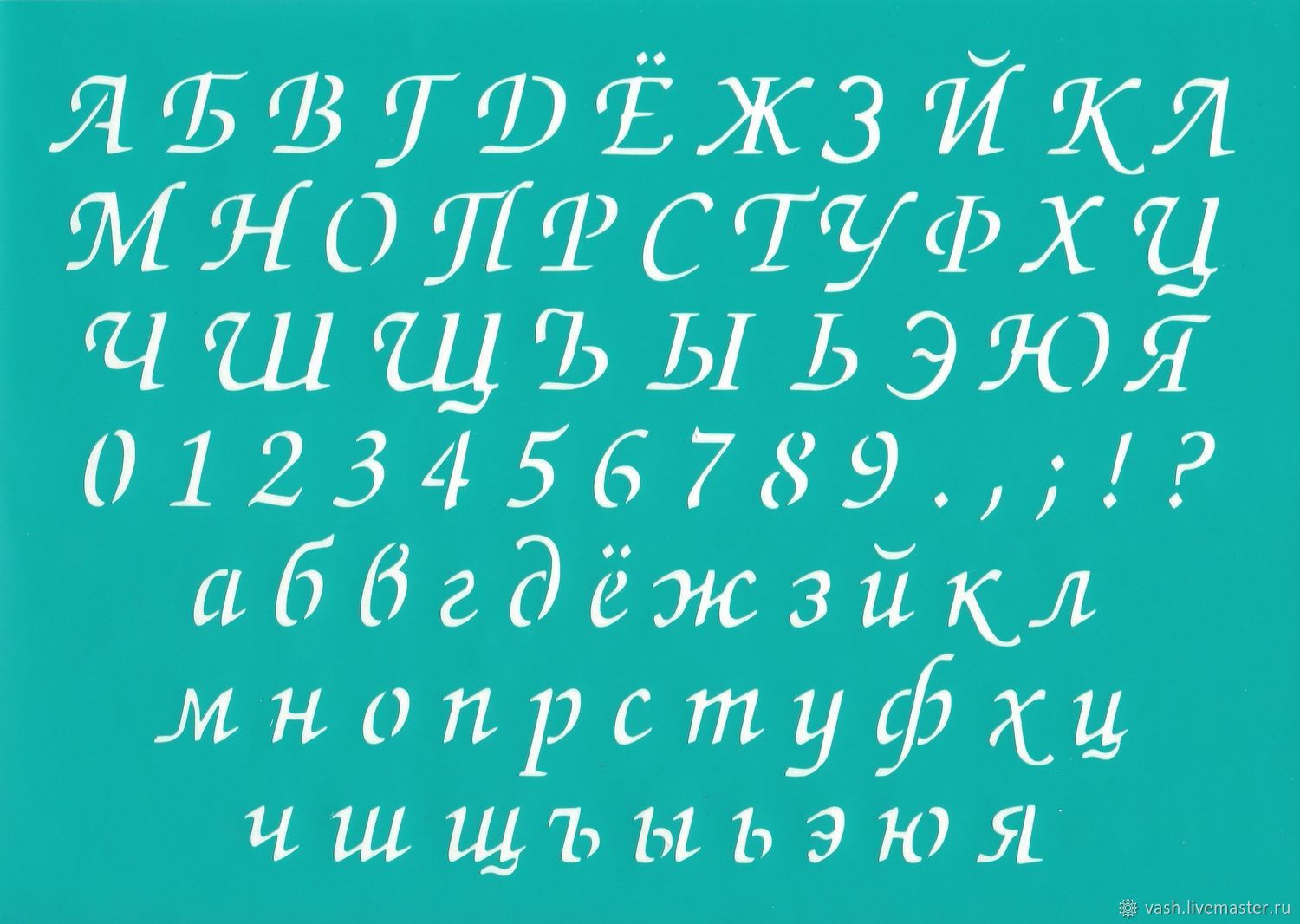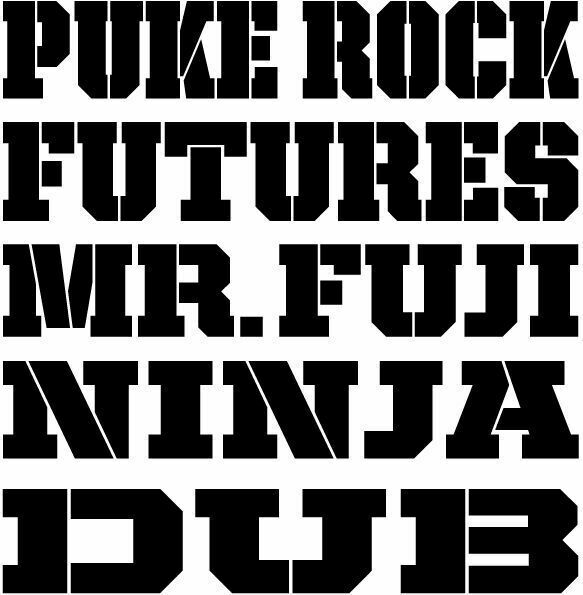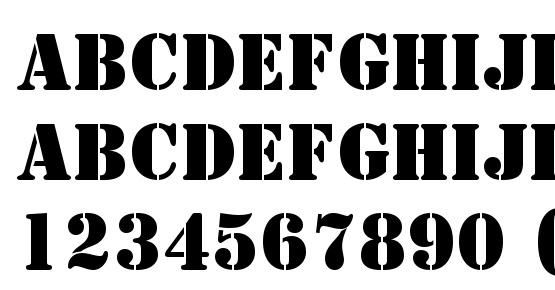
Вензельные буквы русского алфавита трафарет
Трафареты букв – это шаблон формата А4 для распечатки и вырезания из бумаги. Полученный трафарет готов для многократного использования, просто нанесите на него краску тонким слоем. Буквы алфавита в основном используются для оформления праздников, а также в рекламной индустрии и для декора своими руками.
Красивый шрифт, большие буквы, печатные и прописные вызовут неподдельный интерес у детей, начните развивать память и стимулировать творческую деятельность ребенка. Канцелярским ножом аккуратно по контуру вырежьте трафарет, покажите, как равномерно наносится краска. Это поможет сформировать первое представление об алфавите.
Трафареты и шаблоны букв русского алфавита для вырезания из бумаги помогут вам красиво и быстро нанести надпись на любую поверхность. Графическое оформление имеет большое значение в подготовке к праздникам, мероприятиям или презентации. С помощью буквенного трафарета можно оформить стенды, плакаты, стен газеты, рекламу, декорировать интерьер и нанести поздравительные надписи к любым праздникам.
Трафареты и шаблоны русских букв можно бесплатно скачать и распечатать в любом удобном для вас формате. Здесь вы найдете печатные, прописные, строчные и заглавные буквы разных стилей и тематик. А так же красивые трафареты русских букв с завитушками, вензелями и ажурным узором.
Трафаретные шрифты русских букв удивят вас своим разнообразием. Они могут быть в Кириллическом, Декоративном, Художественном, Каллиграфическом, Восточном, Готическом, Арабском, Итальянском и других стилях. Особой популярностью пользуются простые классические шрифты, с витиеватыми буквами.
Трафареты букв, входящих в русский алфавит, используются для создания текста на различных поверхностях. Название «трафарет» происходит от traforetto (итал.), что обозначает «поверхность с отверстием». Чтобы получить готовый трафарет, понадобится только качественный шаблон из интернета, бумага (подойдет любой формат) и принтер. Остается только распечатать изображение.
Вырезание осуществляется одним из двух методов.
Вырезают внутреннюю часть символа: буква или цифра остается пустой. Если шрифт нужен для декорации – внутреннюю часть аккуратно вырезают полностью. Потом красивый заглавный или строчный символ используют для составления слов.
Вопрос о том, как сделать трафарет в программе Microsoft Word, интересует многих пользователей. Проблема в том, что найти на него вменяемый ответ на просторах интернета не так уж и просто. Если и вас интересует эта тема, вы обратились по адресу, но для начала давайте разберемся, что представляет собой трафарет.
Трафарет — это «продырявленная пластинка», по крайней мере, таково значение этого слова в точном переводе с итальянского. Кратко о том, как сделать такую «пластинку» мы расскажем во второй половине этой статьи, а непосредственно ниже мы поделимся с вами тем, как создать основу для традиционного трафарета в Ворде.
Если вы готовы серьезно заморочиться, параллельно подключив фантазию, для создания трафарета вполне можно использовать любой шрифт, представленный в стандартном наборе программы.
Главное, когда он будет распечатан на бумаге, сделать перемычки — места, которые не будут вырезаться в буквах, ограниченных контуром.
Собственно, если вы готовы так попотеть над трафаретом, непонятно, зачем вам наша инструкция, так как в вашем распоряжении есть все шрифты MS Word. Выбираете понравившийся, пишите слово или набираете алфавит и печатаете на принтере, а затем вырезаете их по контуру, не забывая о перемычках.
Если же вы не готовы тратить столько сил, времени и энергии и трафарет классического вида вас вполне устраивает, наша с вами задача — найти, скачать и установить тот самый классический трафаретный шрифт. От изнурительного поиска мы готовы вас избавить — мы все нашли самостоятельно.
Шрифт Trafaret Kit Transparent полностью имитирует старые добрые советские трафареты ТШ-1 с одним приятным бонусом — помимо русского языка в нем есть еще и английский, а также ряд других символов, отсутствующих в оригинале. Скачать его можно сайта автора.
Создание основы для трафарета
Выберите Trafaret Kit Transparent из списка доступных в Ворде шрифтов и создайте в нем нужную надпись. Если же вам нужен алфавитный трафарет, напишите на странице документа алфавит. По необходимости можно добавить и другие символы.
Стандартная книжная ориентация листа в Ворде — не самое подходящее решение для создания трафарета. На альбомной странице он будет смотреться более привычно. Изменить положение страницы поможет наша инструкция.
Теперь текст нужно отформатировать. Задайте подходящий размер, выберите подходящее положение на странице, установите достаточные отступы и интервалы, как между буквами, так и между словами. Наша инструкция поможет вам все это сделать.